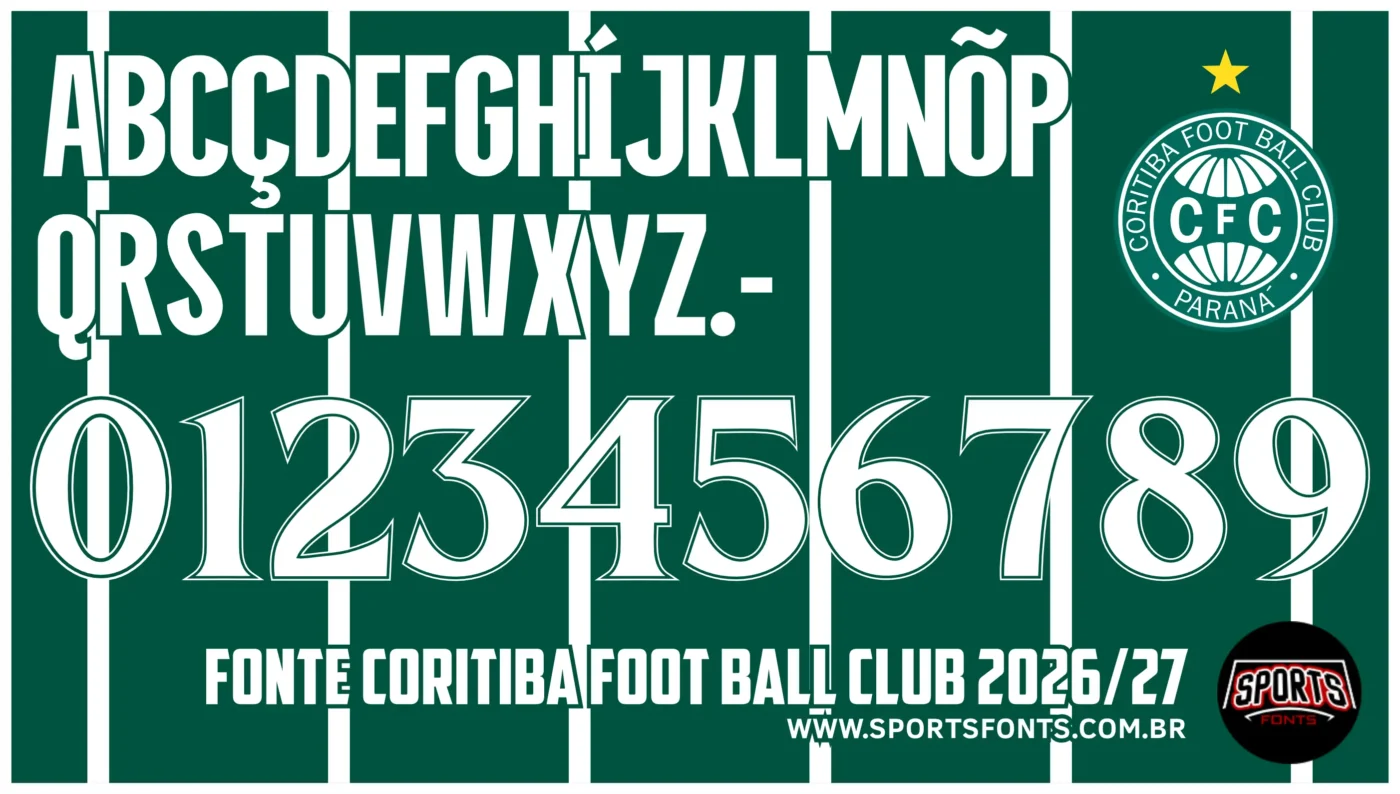
Acabei de finalizar a vetorização da fonte Coritiba Foot Ball Club 2026/27, uma tipografia esportiva inspirada no visual do Coxa. Trata-se de uma versão própria, agora disponível em formato vetorial de alta qualidade.
fonte Coritiba 2026/27
Características da fonte Coritiba 2026/27
• Alfabeto completo com acentos e caracteres especiais (ç, ã, õ, etc.)
• Números de 0 a 9 em estilo bold e esportivo
• Contornos limpos e boa legibilidade
• Visual inspirado na tipografia utilizada pelo Coritiba Foot Ball Club
Fonte Coritiba Foot Ball Club 2026/27 – versão própria e vetorizada.